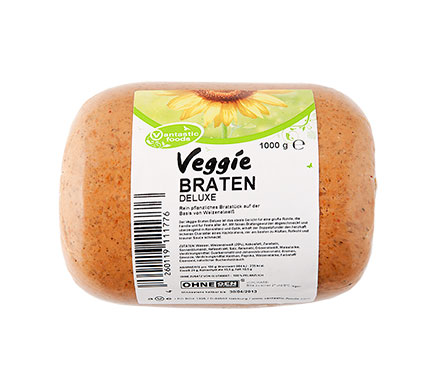
Braucht es am Zeilenende jeweils ein Komma? Kann man Vegibraten schreiben, oder gibt es einen besseren Begriff?
Muss man Dessert schreiben oder nicht?
leichte Suppe, kleiner russischer Salatteller,
Kalbsbraten (Vegibraten), verschiedene Saisongemüse,
Bircherkartoffeln und kleine «Bratherdöpfeli»,
Dessert: russische Crème, Kaffee oder Tee
Ich würde die drei (?) Gänge optisch voneinander absetzen und wenn’s „nur“ eine Leerzeile ist. Das Komma am Zeilenende dann nur innerhalb eines Ganges und „Dessert“ finde ich über, zumal du auch „Vorspeise“ und „Hauptgang“ nicht schreibst ;-) Im Deutschen gehören die Guillmets übrigens andersrum – eigentlich. „Vegibraten“ finde ich nicht ganz so schön und wenn der eine Alternative ist, würde ich das nicht im Klammern – das wäre eher eine Ergänzung/Erklärung – sondern mit „oder“ oder nem Schrägstrich abtrennen. Am Anfang der Zeile würde ich außerdem groß schreiben. Also so:
Leichte Suppe, kleiner russischer Salatteller
Braten vom Kalb oder vegetarisch, verschiedene Saisongemüse,
Bircherkartoffeln und kleine »Bratherdöpfeli«
Russische Crème, Kaffee oder Tee
Wenn du willst (und den Platz hast) kannst du die Leerräume vergrößern und irgendwelche Schmuckelemente oder ne feine kurze Line dort unterbringen. Man könnte auch überlegen, die Gänge noch etwas mehr als Satz zu beschreiben, zum Beispiel (keine Ahnung, ob vor „dazu“ ein Komma muss oder nicht …):
Leichte Suppe und ein
kleiner russischer Salatteller
Braten vom Kalb oder vegetarisch,
dazu verschiedene Gemüse der Saison sowie
Bircherkartoffeln und kleine »Bratherdöpfeli«
Russische Crème mit einem Kaffee oder Tee
Dem ist nichts hinzuzufügen. Außer vielleicht, dass Suppe und Salat Alternativen wären, dann müsste es "oder" heißen. Wenn es denn beides gibt, sind es streng genommen auch verschiedenen Gänge und diese müssten dann wiederum getrennt untereinander genannt werden. Weil "Suppe mit Salat" sehr ungewöhnlich klingt.
Ein bratenförmiges Stück Fleischersatz, z.B. aus Soja, um auch den Vegetariern was anbieten zu können …
Kann man Vegibraten schreiben, oder gibt es einen besseren Begriff?
Muss man Dessert schreiben oder nicht?
Mein gemüseessender Kollege kennt den Begriff nicht, ist er denn in der Gemeinde der Nicht-Tier-Esser eingeführt? Ich habe auf die Schnelle "Veggie-Braten" gefunden, vielleicht geht das für die englischen Gäste.
Also ich, der ich mit einem Vegetarier zusammen lebe, habe den Begriff gleich verstanden. Wie „offiziell“ der ist kann ich aber nicht sagen – auf Chefkoch.de findet man allerdings weder zu „Veggibraten“ noch zu „Vegibraten“ ein Rezept, was dafür spricht, dass es die Begriffe nicht wirklich in der Kochwelt gibt.
Ich finde das Wort aber eh nicht so schön, und es passt vom Klang und seiner „Anmutung“ nicht so recht in den Rest des Menüs, daher habe ich in meinem Vorschlag ja auch umformuliert …
@109: Je nach dem, wie man so ein Fleischersatz zubereitet und aus was selbiger hergestellt ist, kann es schon lecker sein. Zumal man dann auch mal ne andere Konsistenz zu beißen bekommt als die von Gemüse ;-) Ich bleibe aber trotzdem bei echtem Fleisch :hammer:
Leichte Suppe und ein
kleiner russischer Salatteller
Braten vom Kalb oder vegetarisch,
dazu verschiedene Gemüse der Saison sowie
Bircherkartoffeln und kleine »Bratherdöpfeli«
Russische Crème mit einem Kaffee oder Tee
»Einem« würde ich weglassen. Ansonsten gefällt mir diese Version am besten.
Je nach dem, wie man so ein Fleischersatz zubereitet und aus was selbiger hergestellt ist, kann es schon lecker sein.
Ja, da hat sich in den letzten (10?) Jahren viel getan. Was früher nur ein geschmacklich manipulierter Sojaklumpen unangenehmer Konsistenz war, kann heute auch für Fleischfans wie mich äußerst lecker sein, mit ganz verschiedenen und interessanten Konsistenzen von cremig bis knackig.
Also ich, der ich mit einem Vegetarier zusammen lebe, habe den Begriff gleich verstanden. Wie „offiziell“ der ist kann ich aber nicht sagen – auf Chefkoch.de findet man allerdings weder zu „Veggibraten“ noch zu „Vegibraten“ ein Rezept, was dafür spricht, dass es die Begriffe nicht wirklich in der Kochwelt gibt.
Ich finde das Wort aber eh nicht so schön, und es passt vom Klang und seiner „Anmutung“ nicht so recht in den Rest des Menüs, daher habe ich in meinem Vorschlag ja auch umformuliert …
@109: Je nach dem, wie man so ein Fleischersatz zubereitet und aus was selbiger hergestellt ist, kann es schon lecker sein. Zumal man dann auch mal ne andere Konsistenz zu beißen bekommt als die von Gemüse ;-) Ich bleibe aber trotzdem bei echtem Fleisch :hammer:
OK, sicherlich kann was selbstgemachtes lecker sein. Seltsamerweise werden of "Fleischbegriffe" für vegetarisches Essen verwendet. Ich esse ab und an ein trocken gereiftes Steak oder gegrillte Poularde .... yummy
Seltsamerweise werden of "Fleischbegriffe" für vegetarisches Essen verwendet.
Also nach dem, was ich an Ersatz bisher auf dem Teller hatte, gelingt es nichtmal irgendeine Fleischsorte nachzuempfinden, insofern ist die Unterscheidung zwischen verschiedenen vegetarischen Fleischsorten (noch) nicht nötig. Dennoch schmecken die Alternativen, nur eben nicht wie Fleisch …
Das man dazu schreibt, aus was der vegetarische Braten ist, ist sicher ganz sinnvoll.